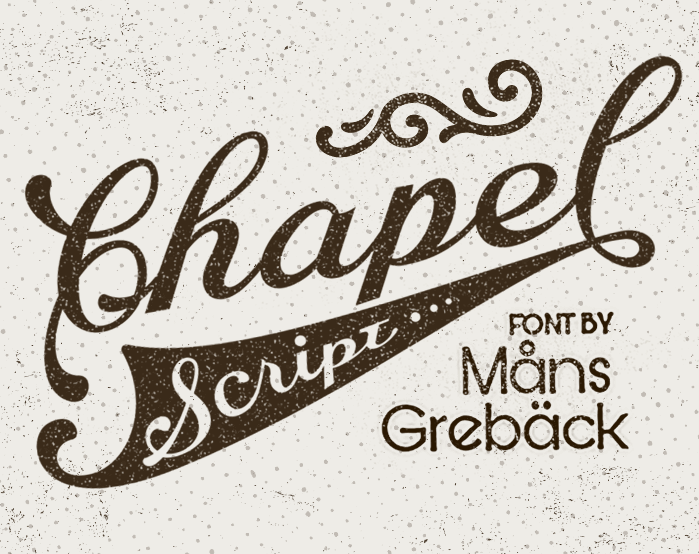
A chapel script font é uma elegante escolha para qualquer projeto de design onde se deseja adicionar um toque de sofisticação ao texto. Com suas linhas delicadas e estilo antiquado, esta fonte é ideal tanto para fins pessoais quanto comerciais. Ela foi desenvolvida pelo designer sueco Måns Grebäck, conhecido por suas belas fuentes chamuscadas e serifadas. Com chapel script font em seu arsenal de ferramentas, você pode criar gráficos incrivelmente detalhados e sofisticados, seja para logotipos elegantes ou texto para publicidade. Suas curvas fluidas e letras bem balanceadas proporcionam um visual arrepiante, tornando esta fonte uma excelente adição aos seu portfólio de recursos gráficos. Para obter o seu license comercial, visite www.mansgreback.com/fonts/chapel-script. Com chapel script font em sua coleção de fones, você poderá explorar novas possibilidades criativas sem limitações comerciais que atrasariam seus projetos mais inspiradores.